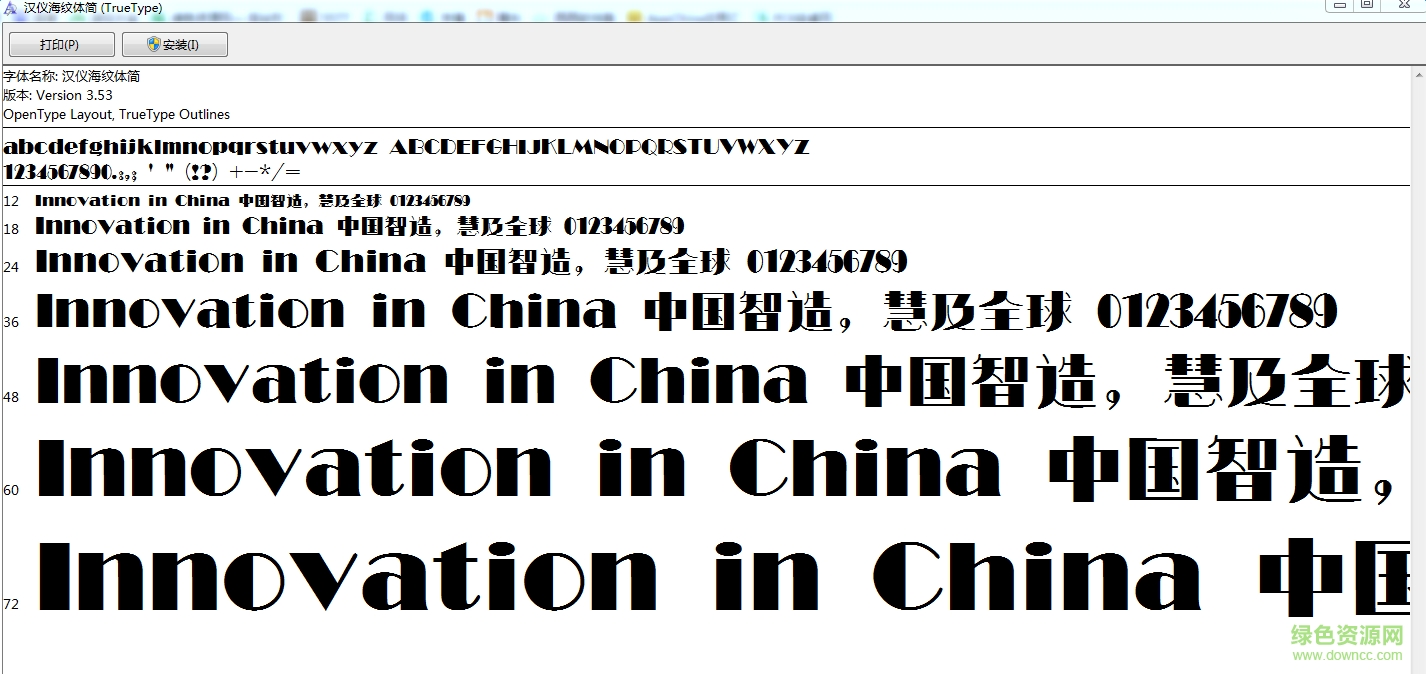
hyg5gj字體又稱漢儀海紋體簡(jiǎn),是一款非常有個(gè)性的漢儀字體,字體借鑒了海浪波紋效果,整體給人感覺大氣而不失風(fēng)趣,非常適合用來(lái)進(jìn)行藝術(shù)創(chuàng)作,喜歡的朋友歡迎下載使用!
hyg5gj字體是一款橫細(xì)豎粗的中文粗體字體,是款比較另類的中文字體,擁有強(qiáng)烈的視覺對(duì)比效果,常用于書法設(shè)計(jì)、名片設(shè)計(jì)、廣告設(shè)計(jì)等行業(yè)領(lǐng)域!